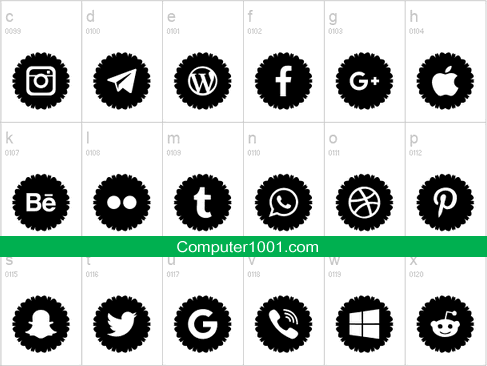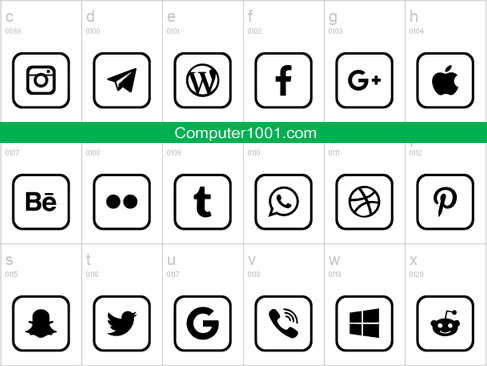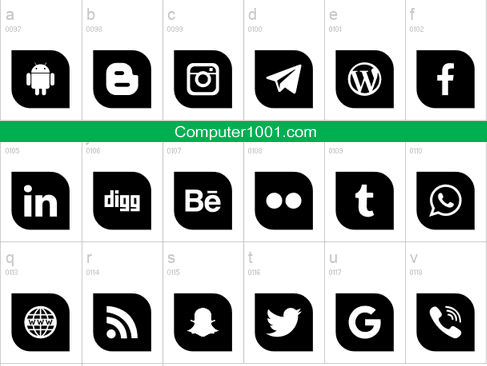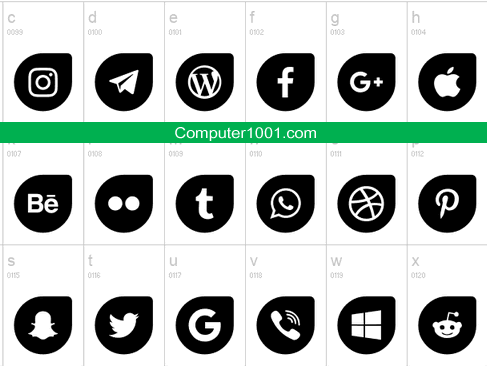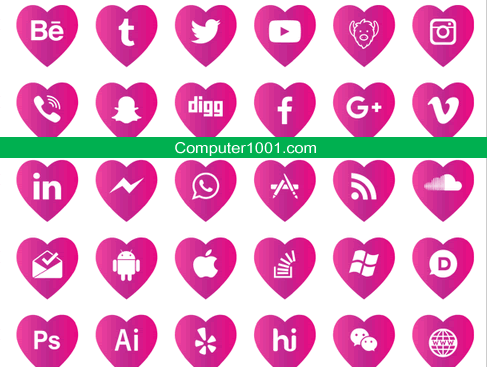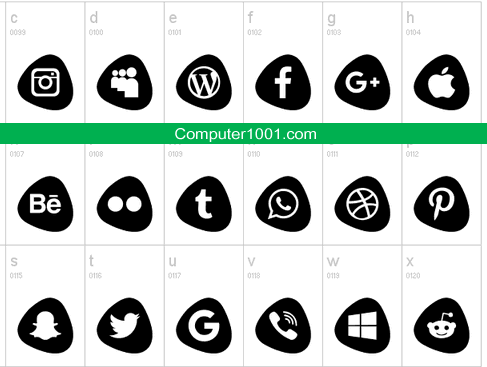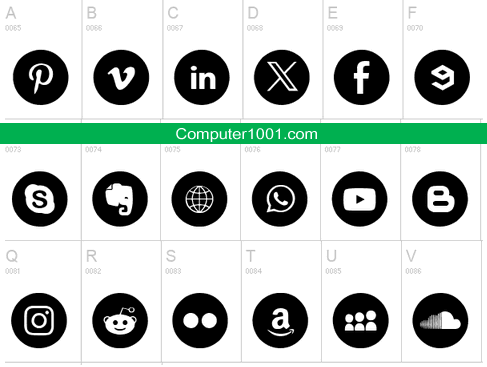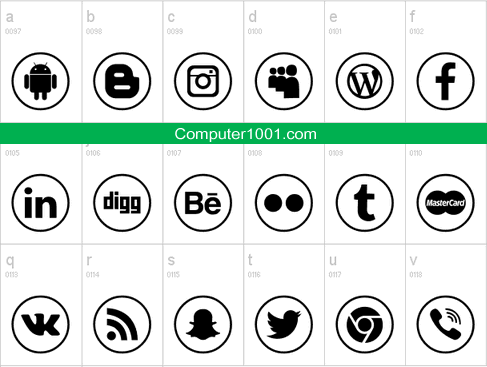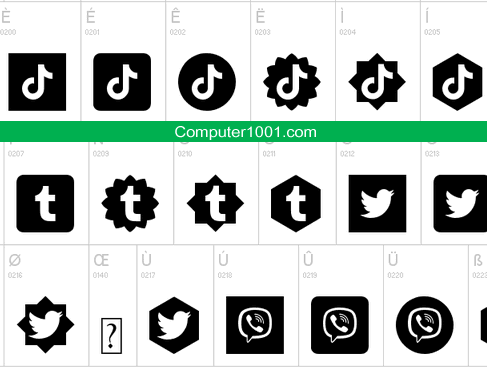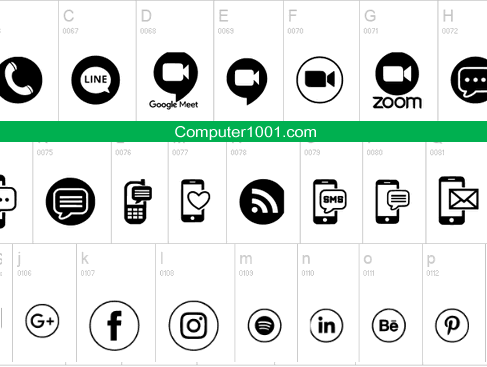
Download gratis font simbol sosial media untuk digunakan di Word, Excel, PowerPoint; atau aplikasi lainnya, seperti Photoshop dan Illustrator.
Font yang disajikan pada artikel ini khusus dipilih yang memiliki gambar logo yang terbaru, contohnya logo Twitter baru yang sekarang berubah jadi X.
Setiap set memiliki 40 – 120 lebih logo simbol sosmed yang populer, dengan berbagai bentuk hiasan bingkai.
Font Social Media Circled
Font sosmed berbentuk lingkaran.
Koleksi logo cukup lengkap, temasuk logo WA, Line, simbol untuk kontak (seperti lokasi, telp / hp, dan email); serta logo Twitter X hitam putih yang merupakan logo baru yang menggantikan logo Twitter lama yang berbentuk burung.
Social Media Circled
Font Sosmed Social Shapes
Font berisi logo sosmed, pesan instan, dan merek terpopuler (Tiktok, Telegram, Sina Weibo, WeChat, Google Play, Apple, Android, dan lain-lain). Semuanya dengan 6 bentuk bingkai.
Social Shapes
Font Social Media
Selain memiliki simbol sosmed yang populer, juga ada simbol wifi, handphone, email, alamat / lokasi, dan website, serta kartu kredit (Mastercard dan Visa) dan sistem pembayaran (Paypal dan Bitcoin).
Sayangnya belum memiliki logo WhatsApp. Jadi harus digabungkan dengan font sosmed yang lain.
Social Media
Font Social Icons
Font sosmed dengan bingkai bentuk scallop.
Sama seperti font di atas, font ini juga memiliki simbol fiverr, Vimeo, ebay, Behance, Tripadvisor, dan Line Messenger.
Social Icons
Font Social Logos Color
Font sosmed ini memiliki bentuk bingkai segitiga reuleaux yang cantik. Tidak ada logo kartu kredit, tapi ada logo WhatsApp.
Social Logos Color
Font Icon Sosmed Type Icons
Font sosial media tanpa bingkai.
Type Icons
Font Sosmed Phone
Font ini memiliki logo media sosial dan telepon yang populer saat ini. Juga ada logo video konferensi seperti Zoom dan Google Meet.
Sosmed Phone
Love Social Media Font
Font sosmed berbentuk hati.
Love Social Media
Font Sosmed Social Circles
Font sosmed berbentuk bulat dengan 2 bentuk bingkai (outline yang tebal dan warna solid).
Social Circles
Font Icons Social Media 2
Font icon sosmed model bulat dengan bingkai aksen gerigi.
Icons Social Media 2
Font Sosmed 120 Logos
Modelnya mirip dengan font di atas, cuma yang ini bewarna solid.
Font 120 Logos
Font Sosmed Icons 2019
Font icon sosmed dengan bingkai outline kotak persegi.
Font 120 Logos
Font Icons Social Media 7
Font sosmed bentuk kotak warna solid.
Icons Social Media 7
Font Icons Social Media 12
Font simbol bentuk droplet. Model yang sama dengan sedikit variasi bisa didapatkan di sini.
Icons Social Media 12
Font Icons Social Media 14
Icons Social Media 12
Font Icons Social Media 1
Icons Social Media 1